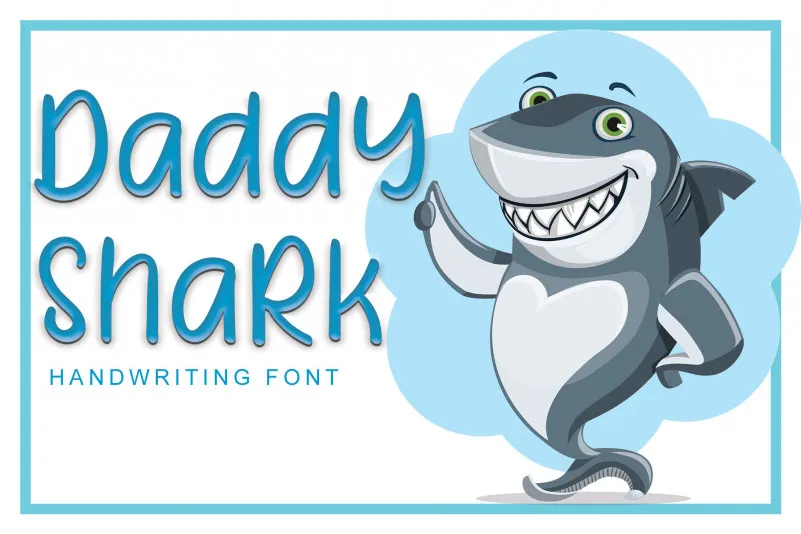
Esta é uma fonte feita à mão com carinho, criada para ser divertida e enriquecedora. O estilo cômico faz dela perfeita para projetos escolares e infanto-juvenis que precisam de um toque leve e alegre. Seja em cartazes educacionais, materiais de sala de aula ou até mesmo em posters de aniversário, ela é uma ótima opção para deixar o seu trabalho brilhar com carinho. Criativa e versátil, esta fonte é perfeita para quem busca um ar descontraído e acolhedor sem abrir mão da qualidade estética que a fonte proporciona. Numa categoria de fontes Display, ela se destaca como uma escolha inteligente para aqueles projetos que precisam soar divertidos e emocionantes.